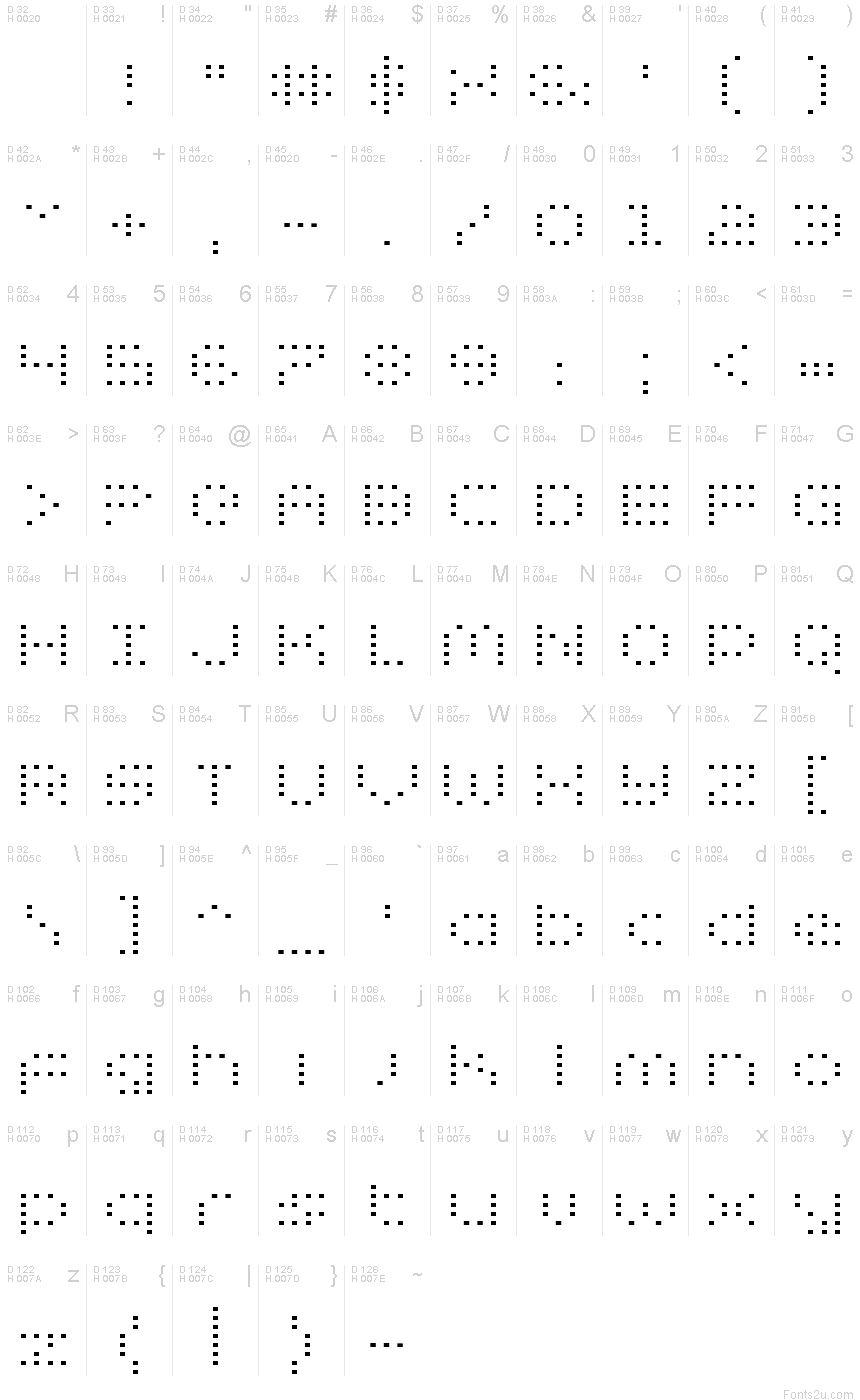
Zado Expanded od Iconian Fonts to darmowy, bitmapowy font typu display o surowym, technicznym charakterze sci-fi, opartym na siatce. Litery są zbudowane z kwadratowych modułów i przerwanych poziomych pasów, dzięki czemu całość przypomina bardziej wyświetlacz sygnałowy, sprzęt do gier retro czy panel skanujący niż zwykły krój pisma.
To naturalny wybór do plakatów w stylu retro-tech, brandingu inspirowanego grami arcade, makiet interfejsów, okładek albumów, plansz tytułowych i krótkich nagłówków, gdzie darmowy font ma szybko zbudować klimat. Użyj go, gdy chcesz, aby krótkie słowa, logotypy czy nagłówki sekcji wyglądały na zakodowane i wygenerowane maszynowo – powtarzalny wzór bloków nadaje nawet prostemu tekstowi surowy, elektroniczny puls.
Zado Expanded